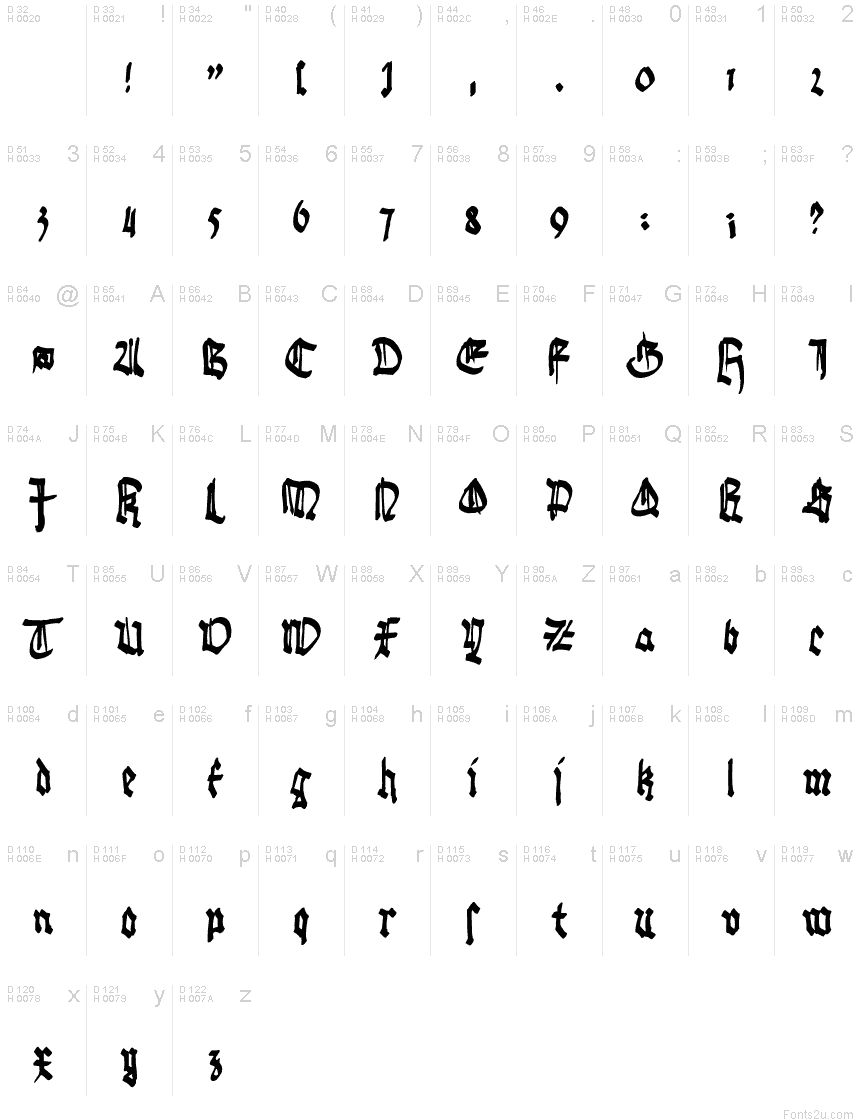
Gothic Bozo di RZY è un font gotico gratuito che sembra inciso con un pennello carico e un bel po' di carattere. I tagli frastagliati, le curve gonfie e i tratti irregolari e schizzati donano a ogni parola un'energia cruda e underground: più una tempesta che una calligrafia. Le lettere si incastrano in un ritmo serrato e incisivo, che risulta aggressivo e artigianale, ben lontano da finiture pulite o da un effetto costume medievale.
Con Gothic Bozo, puoi spingere titoli e loghi al limite per band metal, poster horror, titoli di giochi, grafiche streetwear, fanzine o copertine di libri dall'atmosfera occulta. Questo font gratuito dà il meglio di sé in grande, in grassetto e con spazio per respirare; abbinalo a un sans serif pulito e neutro per il corpo del testo, così la sua texture selvaggia e inchiostrata rimarrà protagonista senza sacrificare la leggibilità.